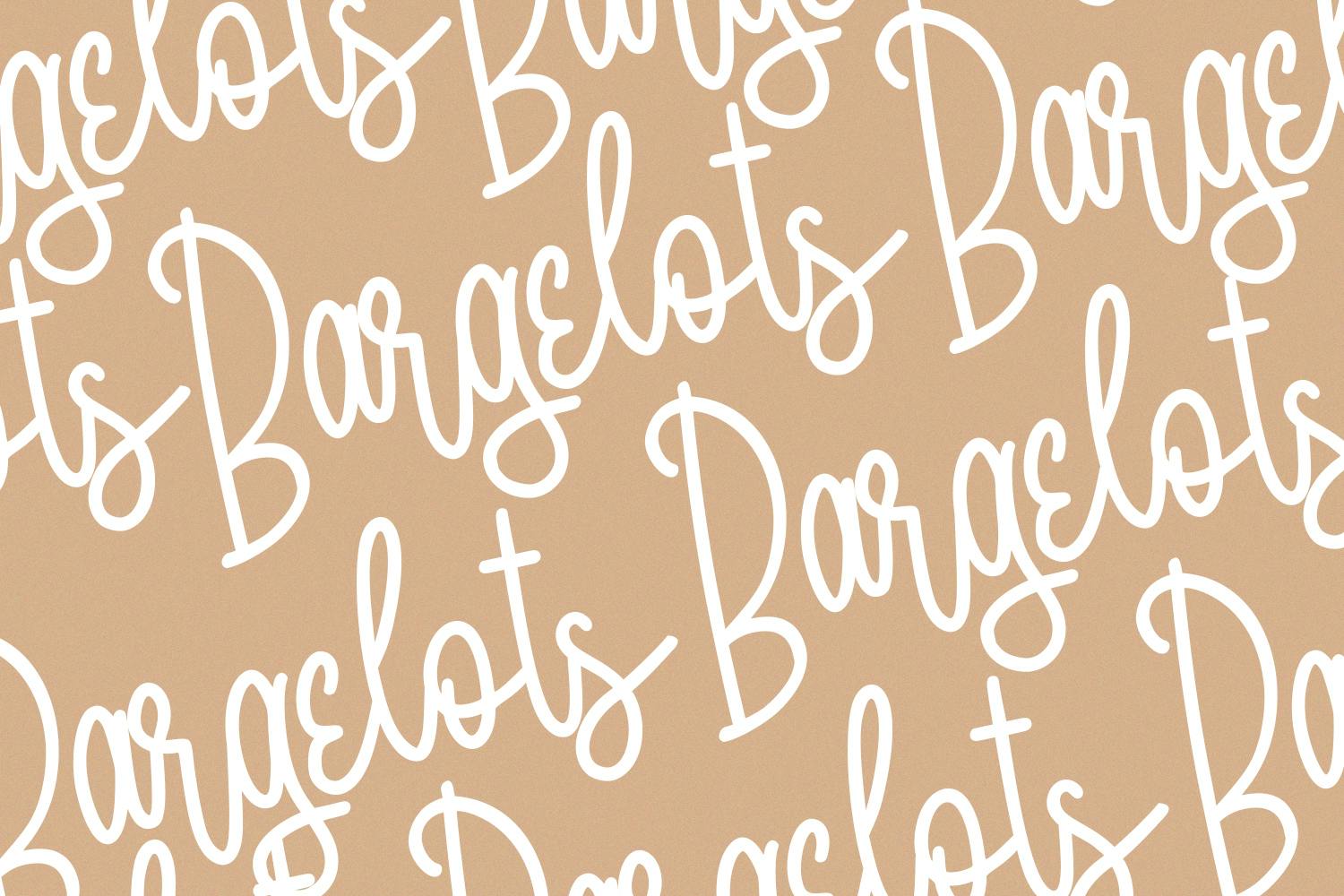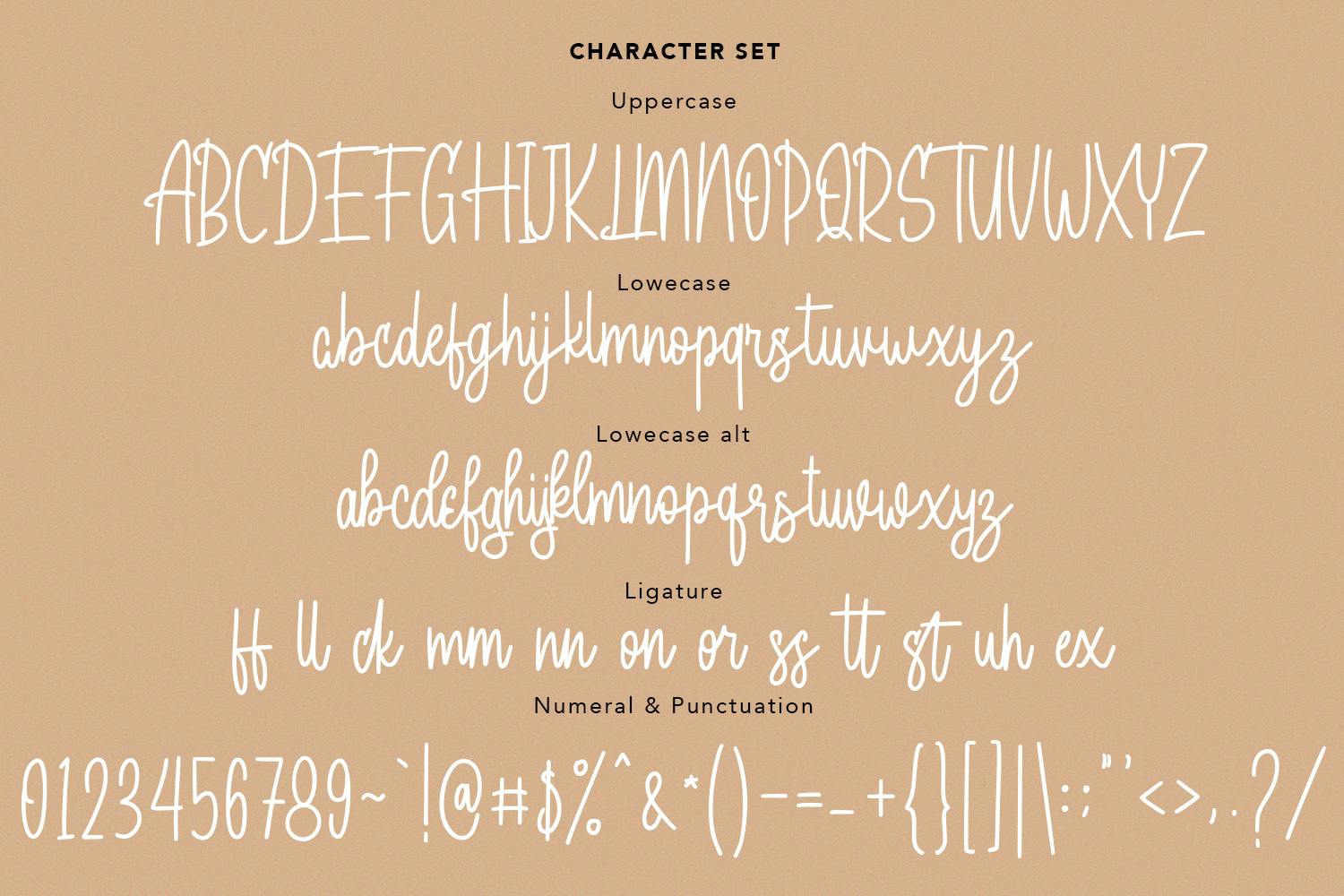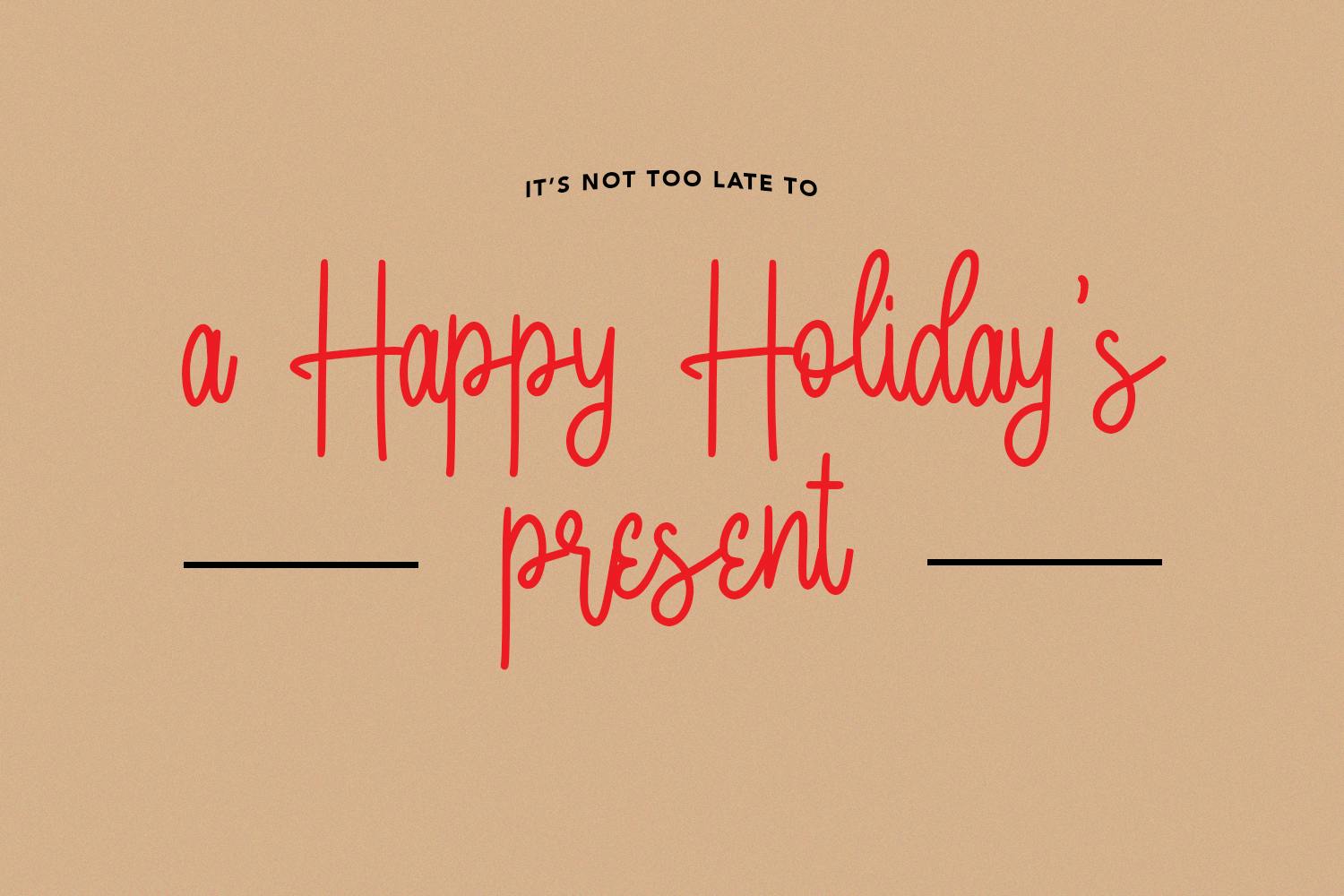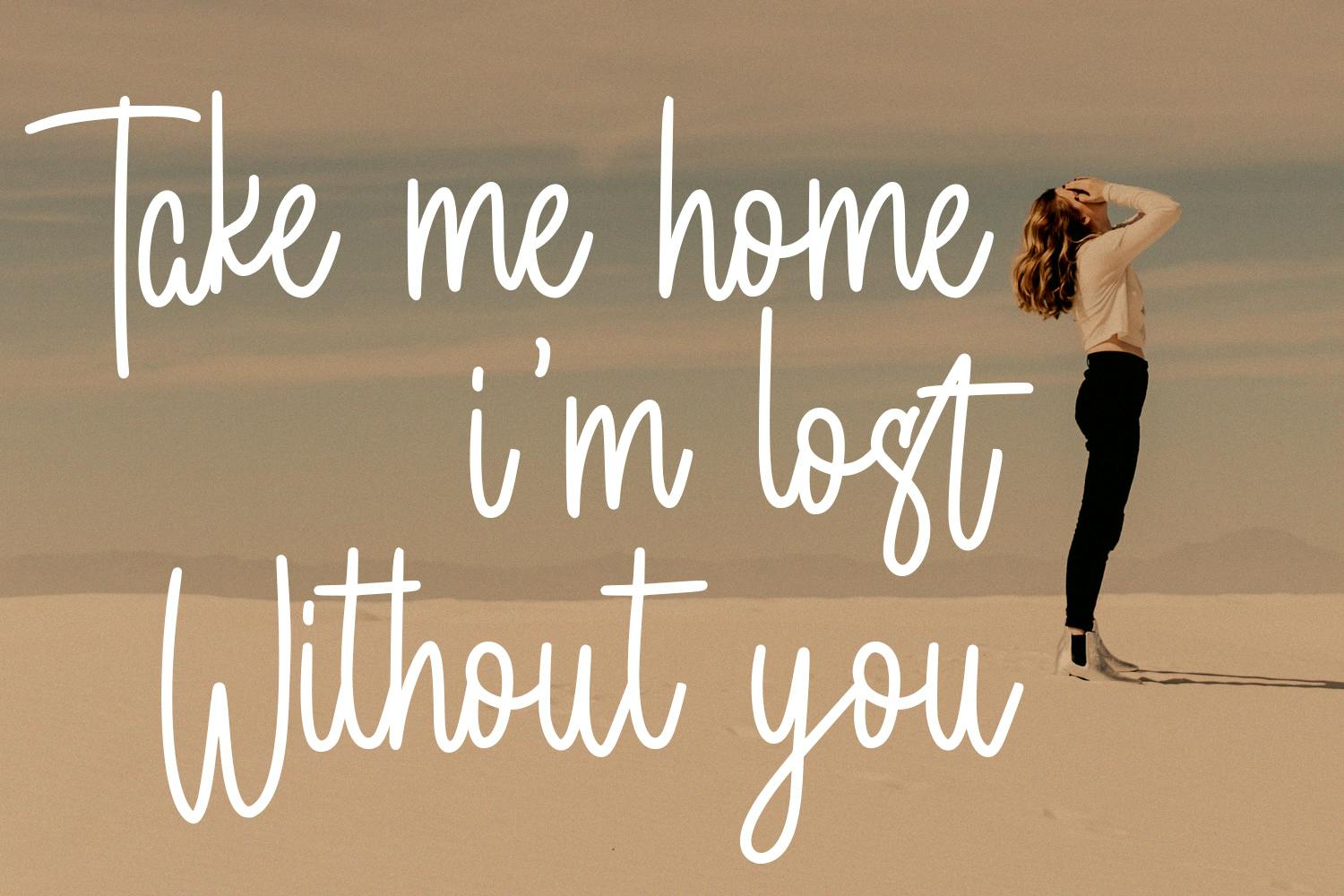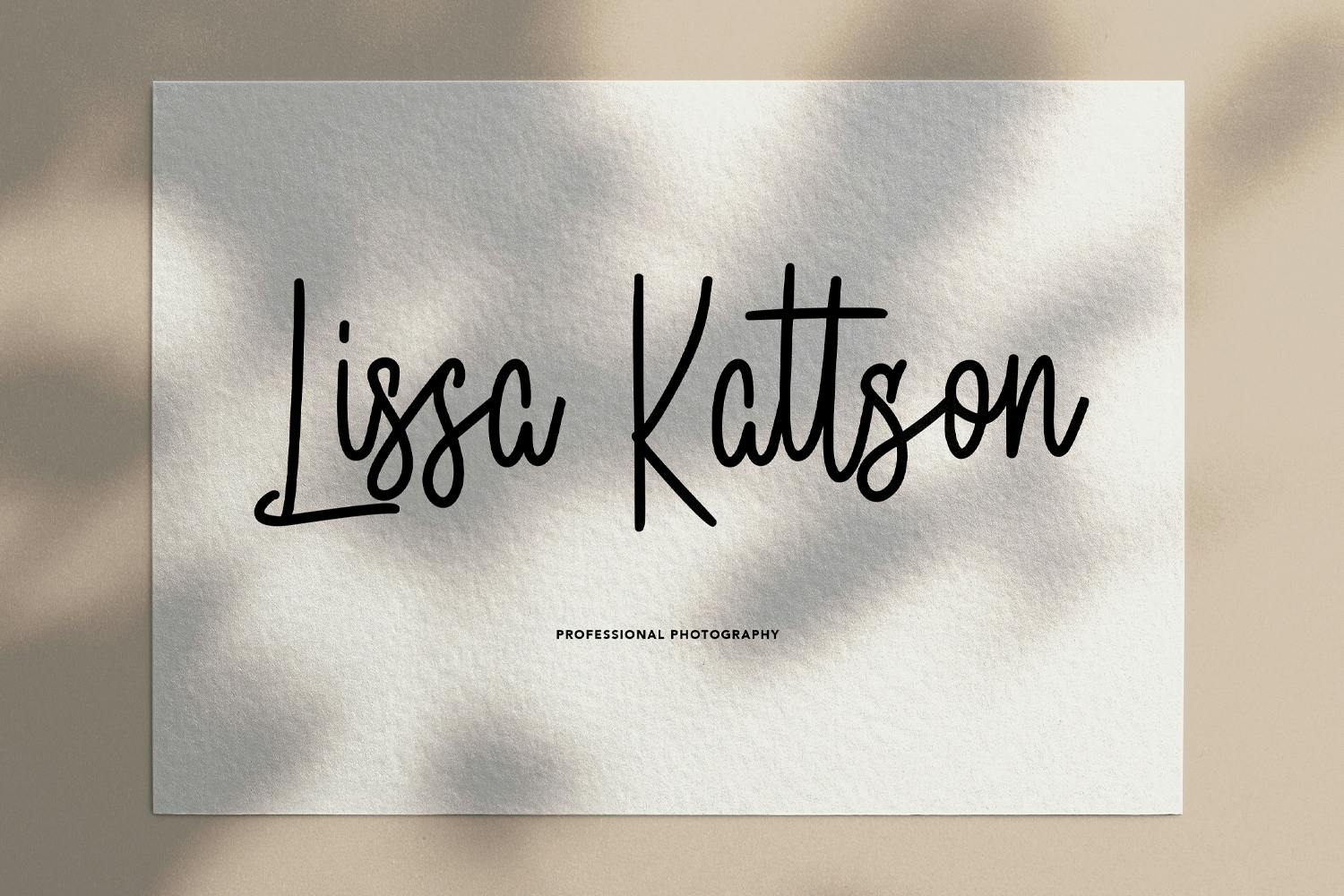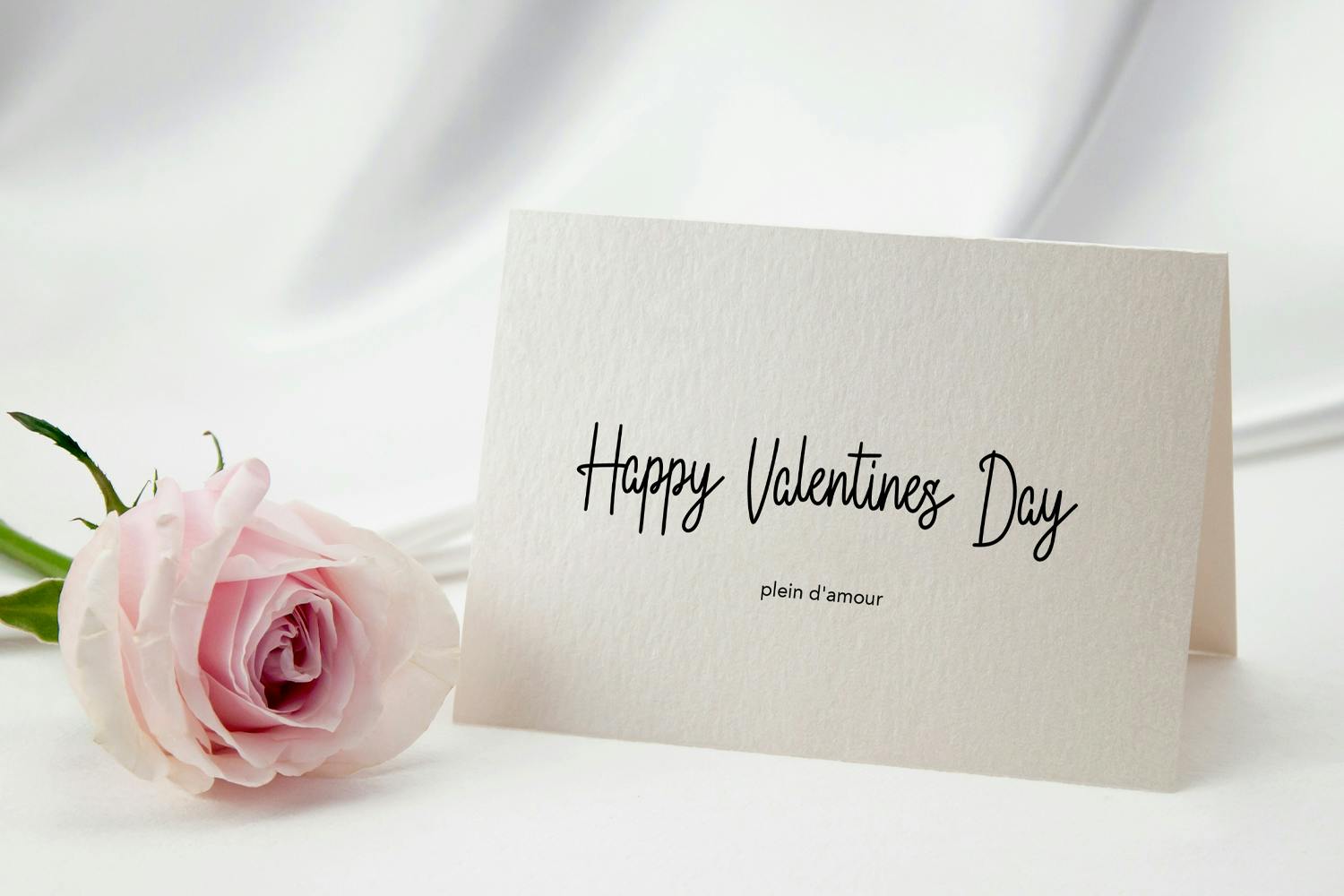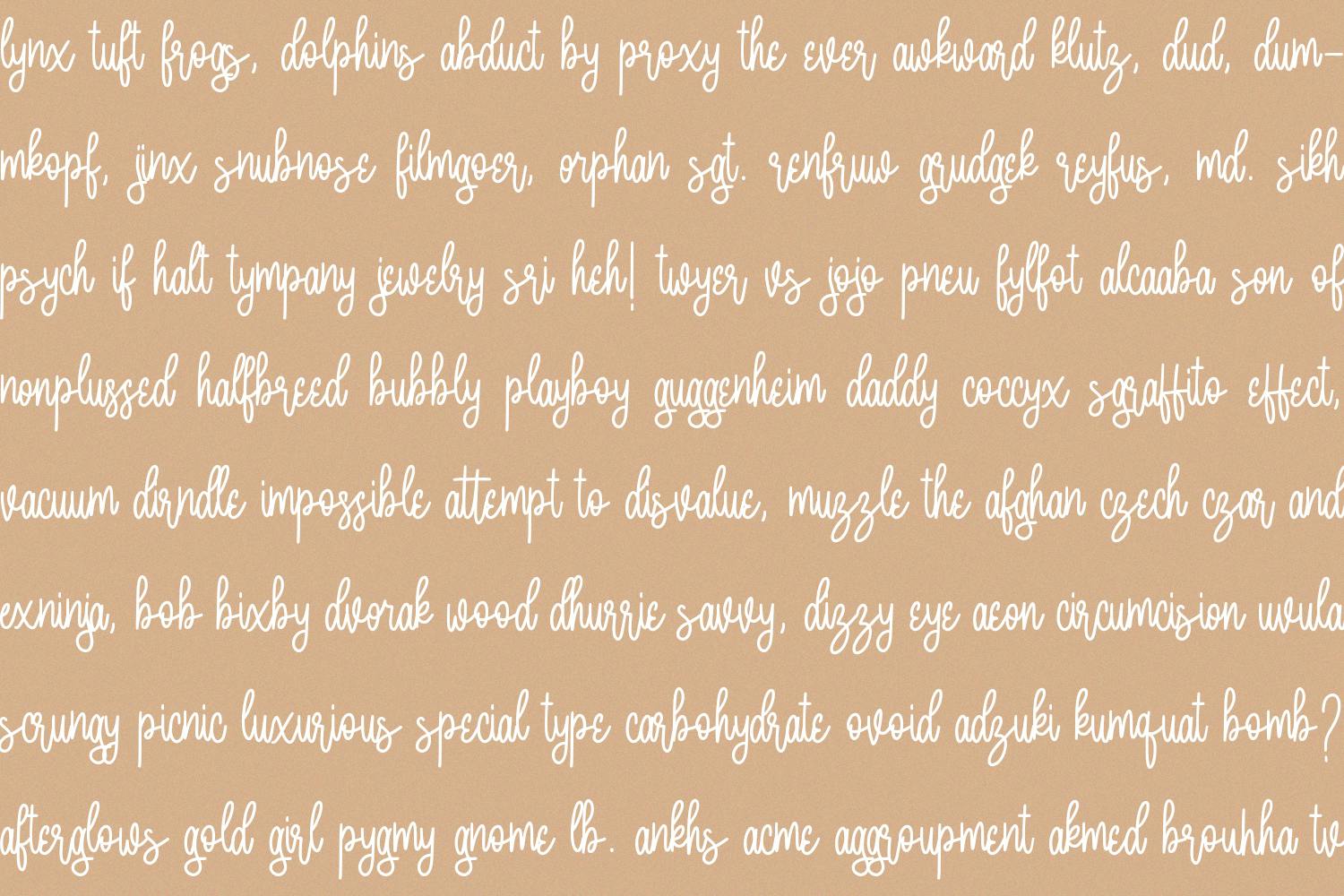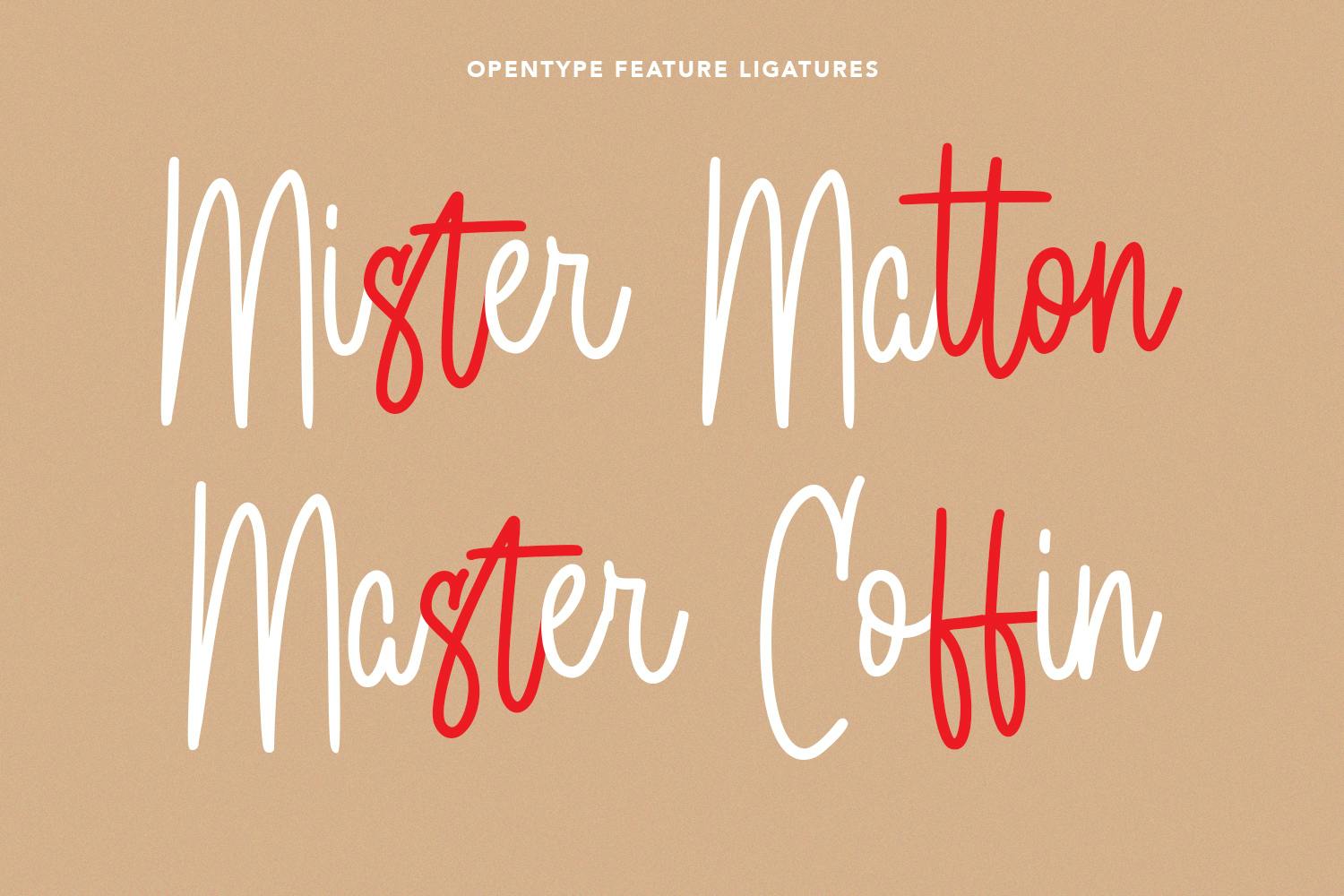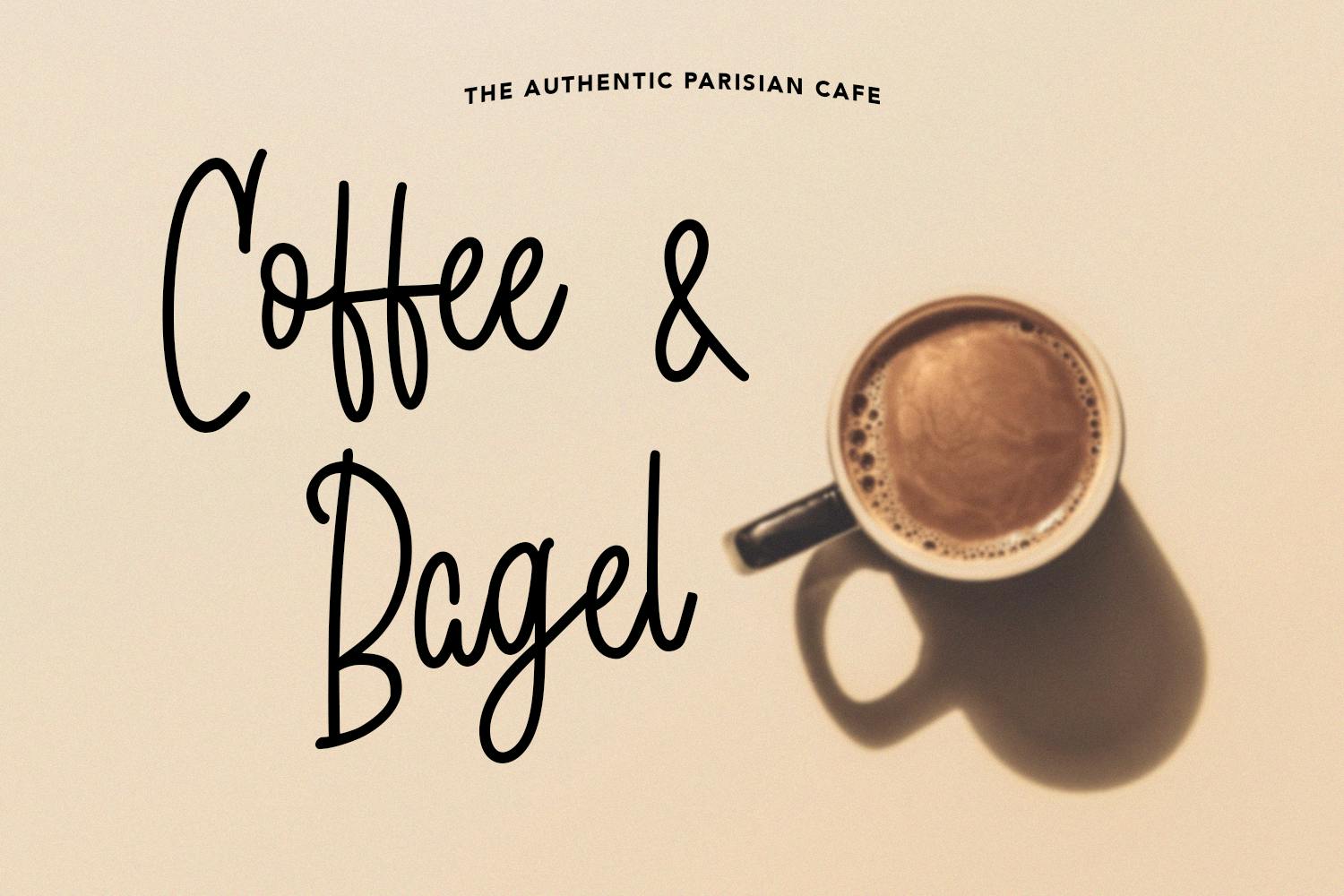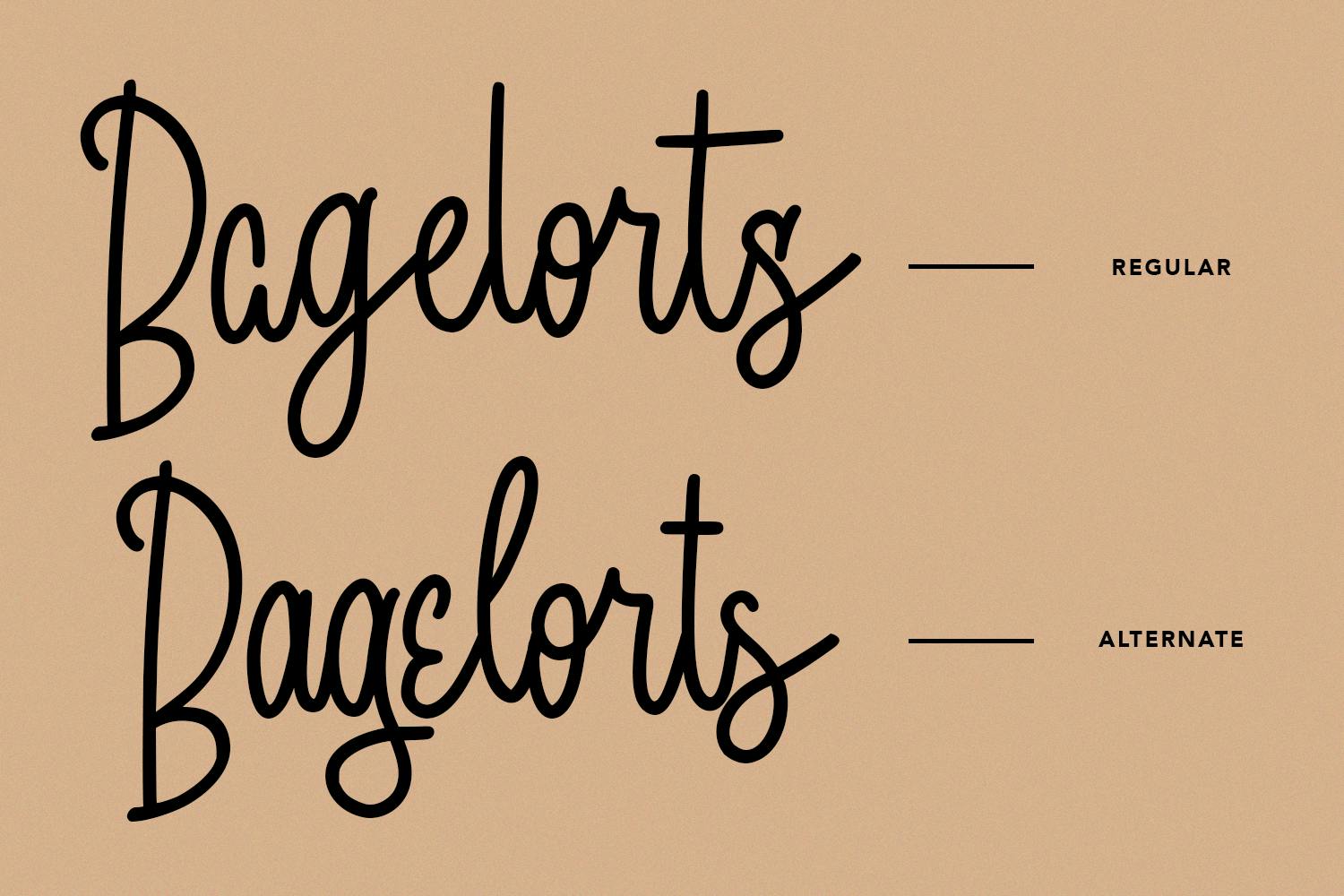
دانلود فونت دست‌نویس Bagelorts برای طراحی‌های خاص
Bagelorts Handwritten Script Font
فونت دست‌نویس Bagelorts، انتخابی ایده‌آل برای طراحی‌های خلاقانه شما.
فونت دست‌نویس Bagelorts
طراحی‌های خود را با احساس واقعی دست‌ساز جلوه دهید. فونت دست‌نویس Bagelorts به‌طور کامل برای لوگو، لوازم‌التحریر، برندینگ، نقل‌قول‌های تایپوگرافی، جلد مجله یا کتاب، سرصفحه وب‌سایت، پوشاک، بسته‌بندی و رستوران‌ها مناسب است.